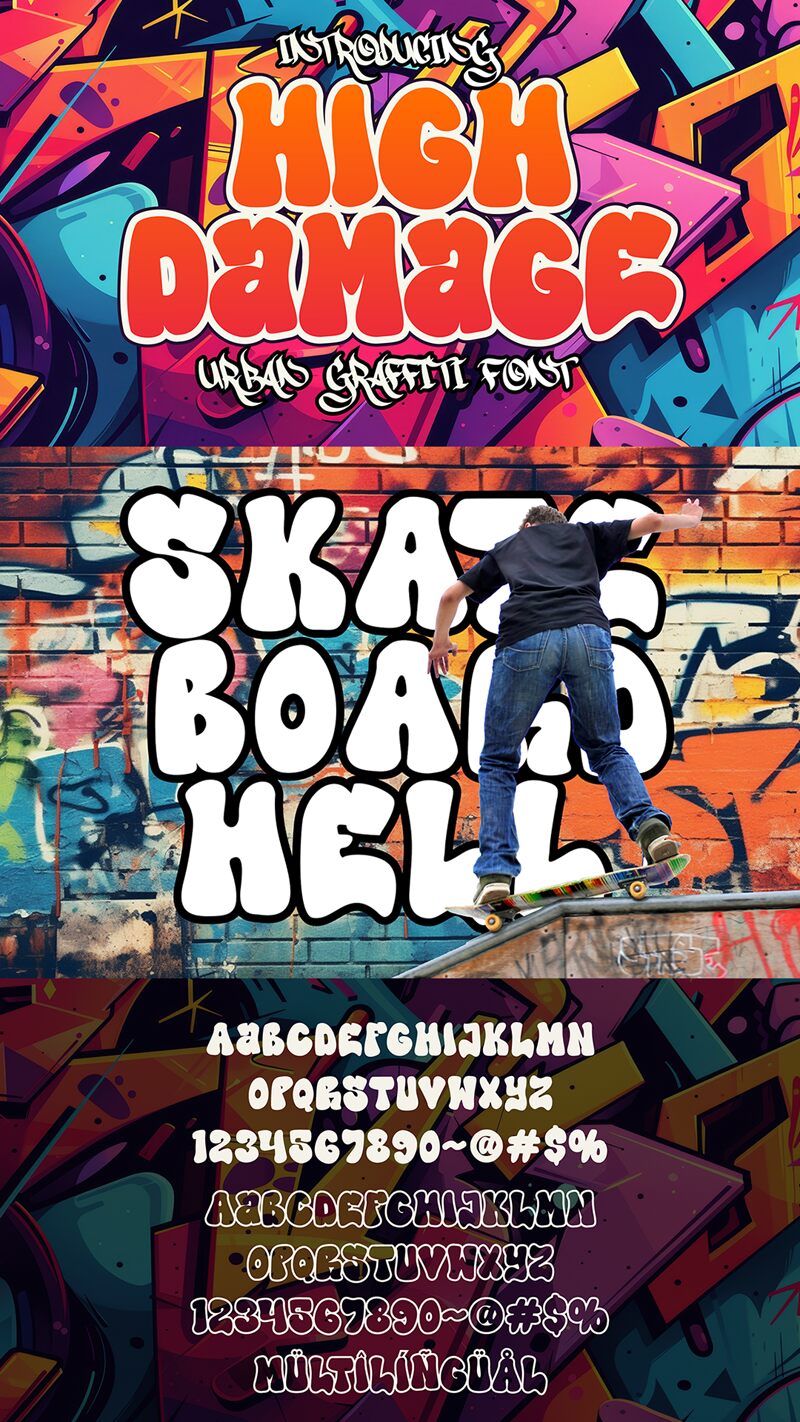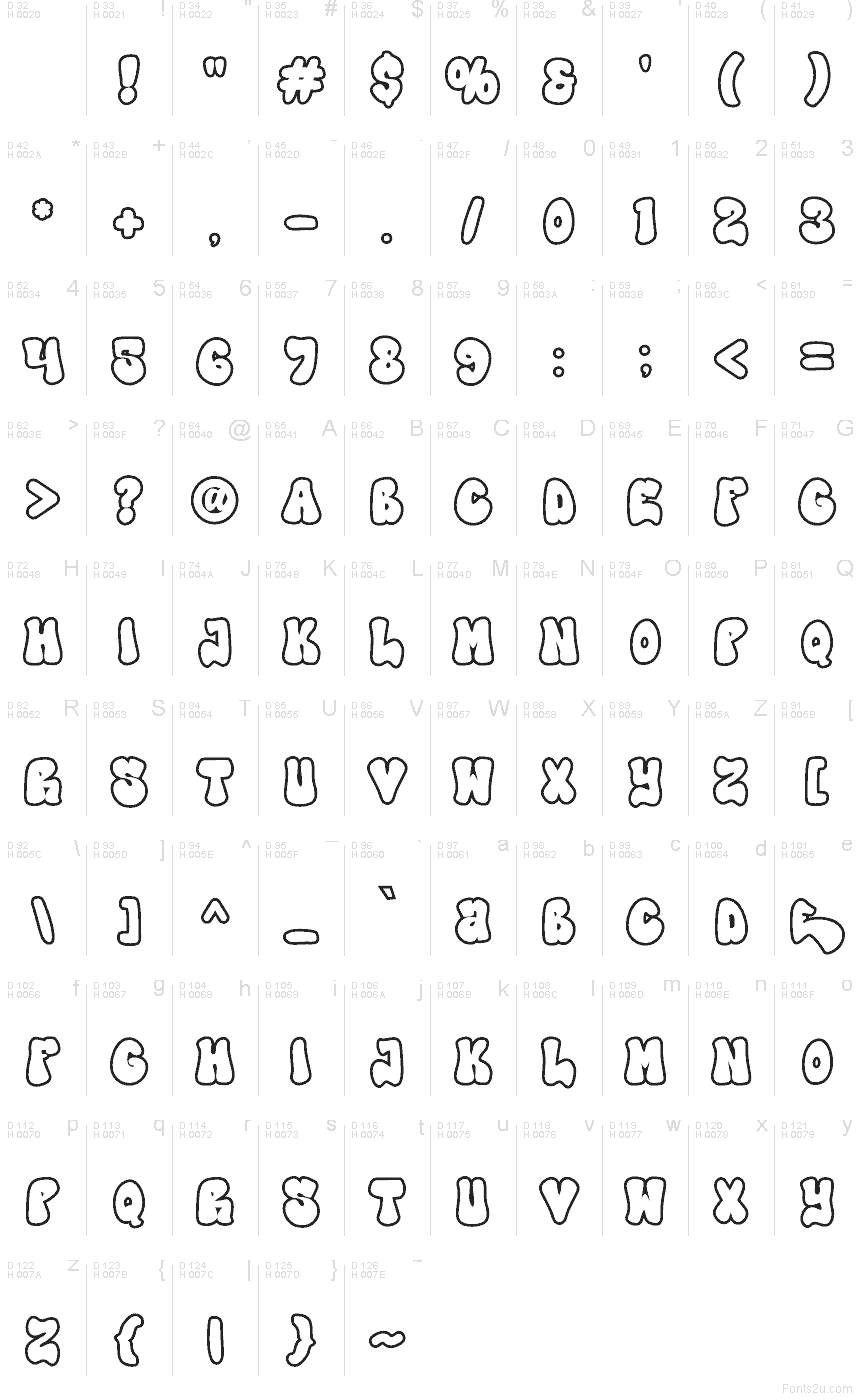
High Damage - Outline, creata da Saepul milah di CikareotypeStudio x figureeStudio, è un font graffiti gratuito caratterizzato da grandi forme morbide e un contorno netto, che ricorda l'inchiostro fresco di un pennarello su un muro. Le lettere appaiono vivaci e dinamiche, con un'oscillazione giocosa e un'ampia spaziatura che mantiene il testo leggibile anche se ingrandito o con un riempimento colorato sul retro.
Con High Damage - Outline, conferirai immediatamente carattere a loghi streetwear, grafiche skate e BMX, set di adesivi, copertine di album, miniature YouTube, volantini di eventi e post social incisivi. Prova ad abbinare questo font gratuito a una semplice sans serif condensata per date e dettagli e lascialo respirare: nei grandi formati, il suo contorno dinamico risalta davvero.